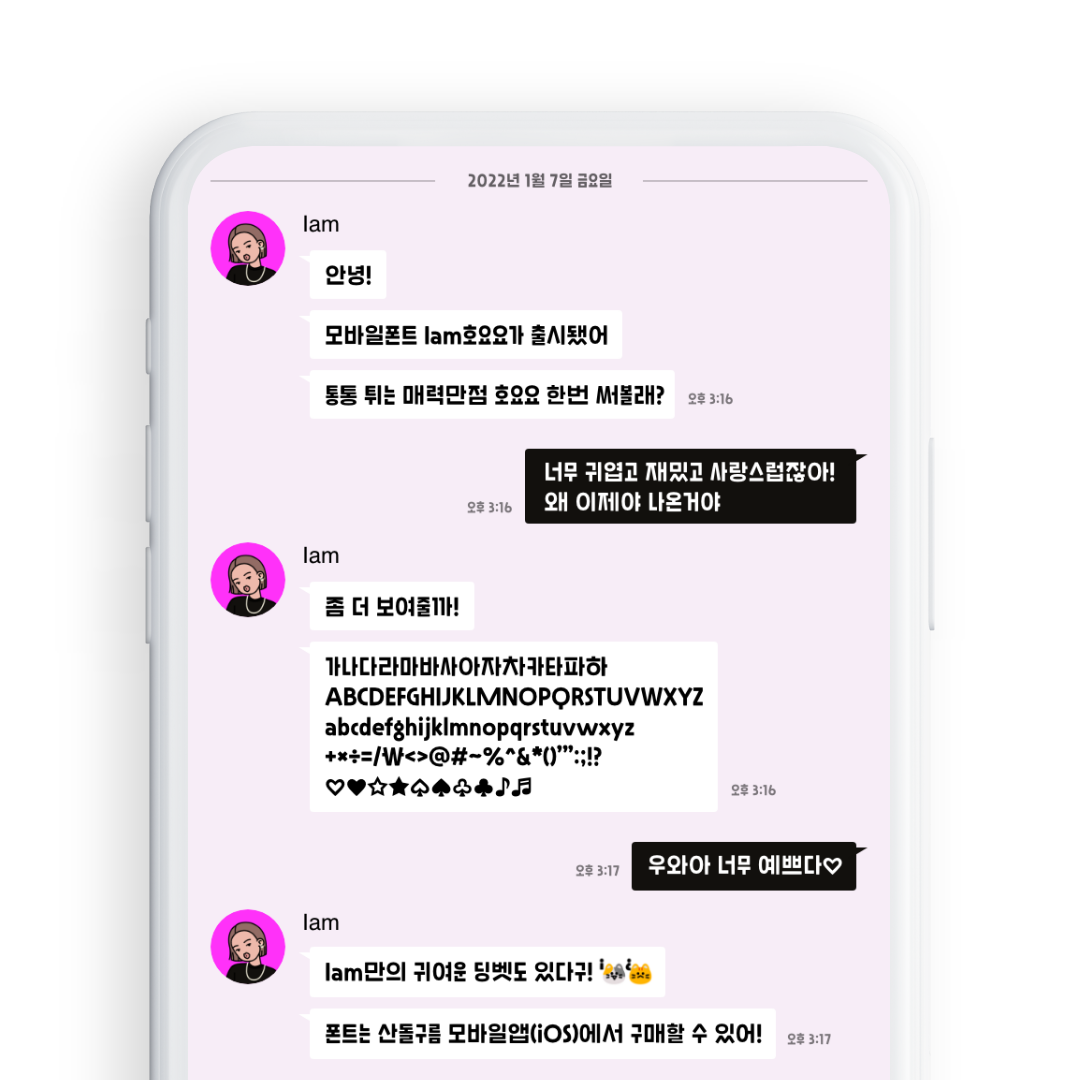
Iam 호요요
Iam 호요요는 모바일 전용으로 제작된 폰트입니다.
꽉 찬 네모꼴의 호요요는 타이핑 할 경우 예측할 수 없는 가변폭을 가지고 있어요. 같은 글자를 반복 입력했을 때 다른 폭의 글자를 경험해 보세요! (ex. 호요요, 댕댕이, 바나나 등)
Iam 호요요에는 귀여운 고양이 딩벳이 숨어있어요. 키패드에서 물음표와 느낌표를 꾹 눌러서 ¿ 역물음표와 ¡ 역느낌표를 타이핑 해보세요!